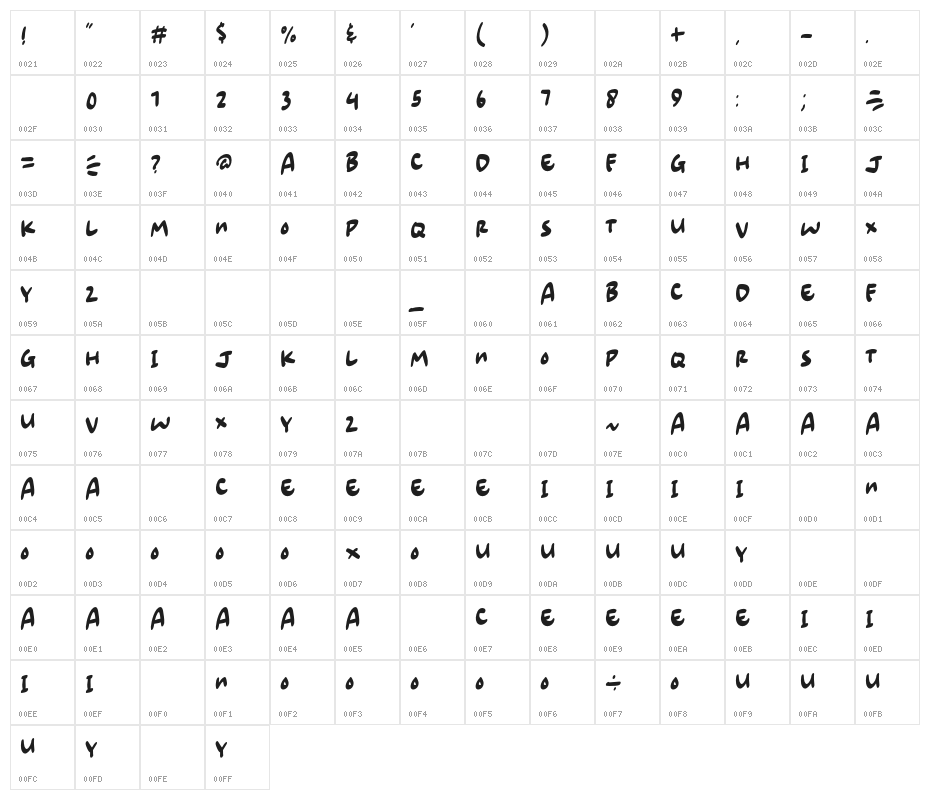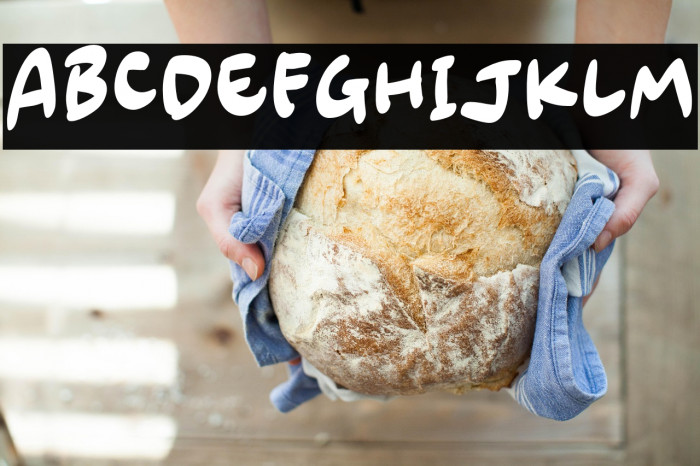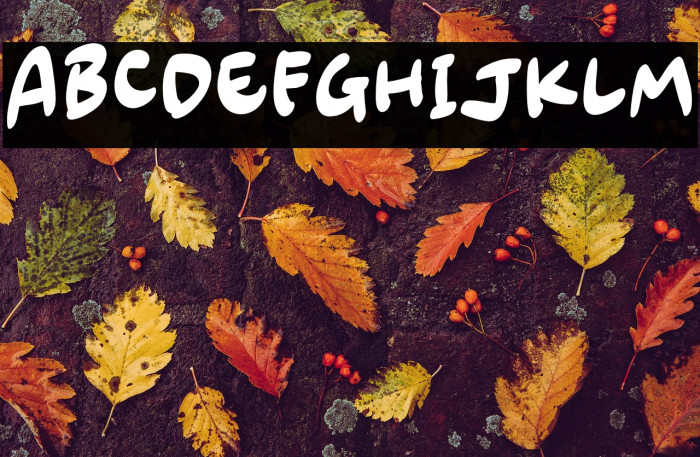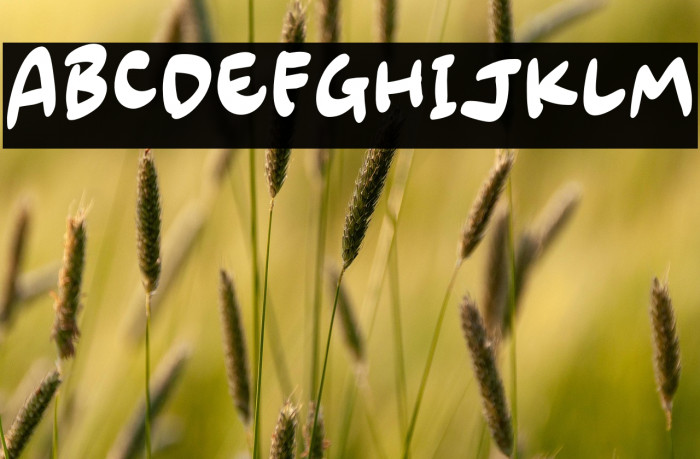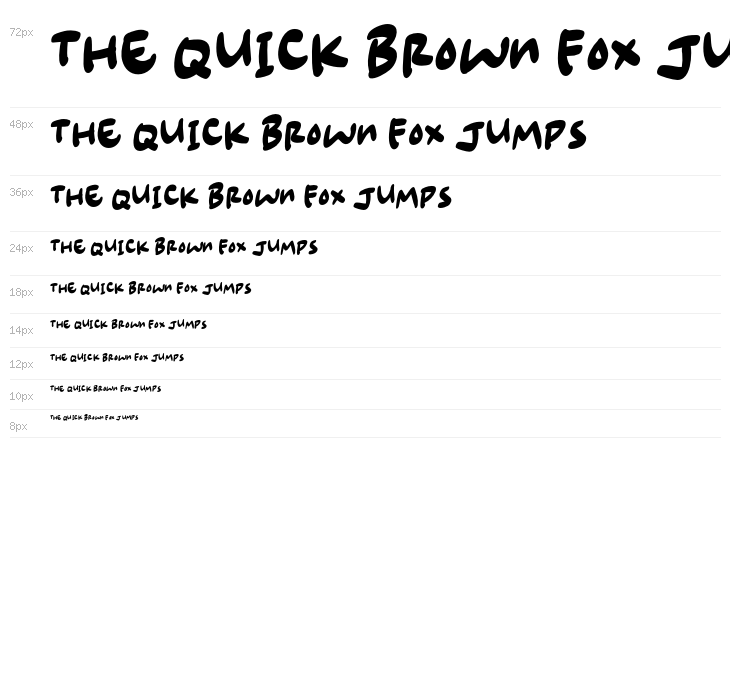
Amazing Swash Font
AMAZING-SWASH MAIUSCOLE
AMAZING-SWASH MINUSCOLO
AMAZING-SWASH ALTRI CARATTERI
| Nome | Amazing Swash |
| Stile generale | Playful, Casual |
| Caso d'uso | Headlines, Logos, Invitations |
| Progetti proposti | Ideal for greeting cards, invitations, posters, and branding that requires a personal and lively touch. |